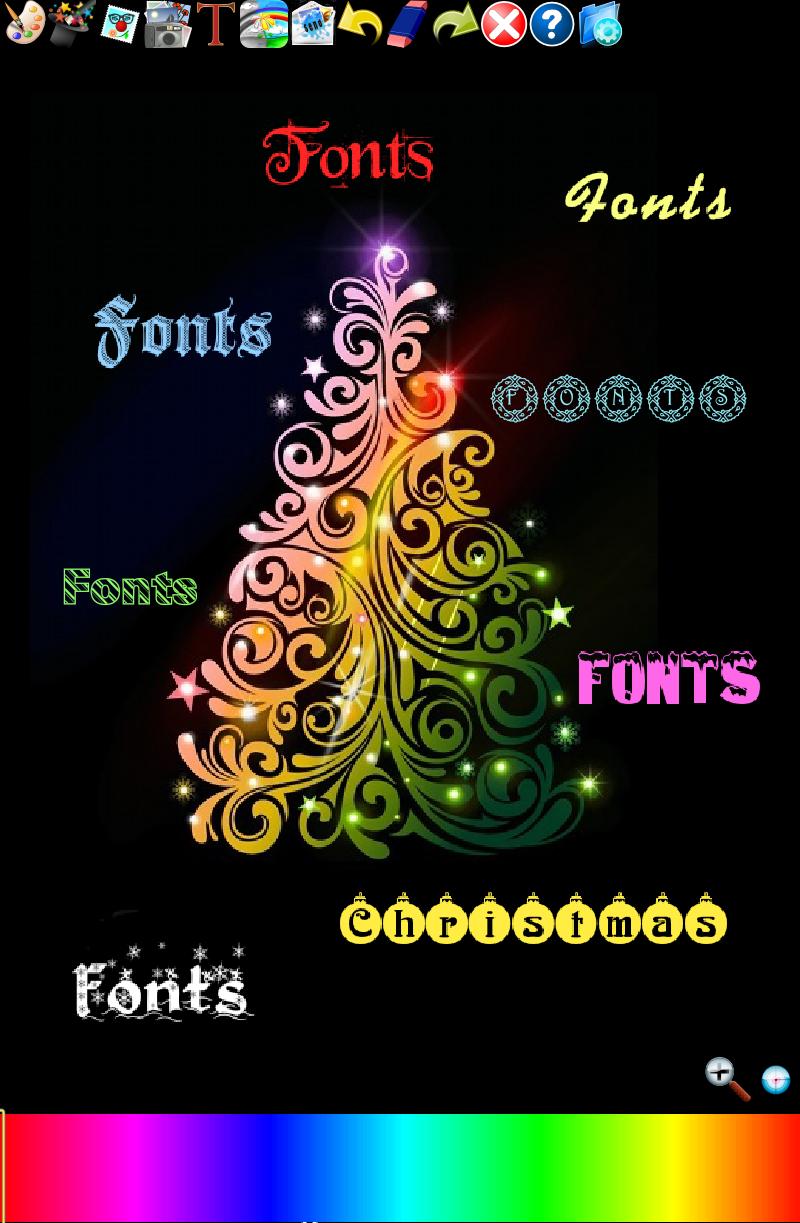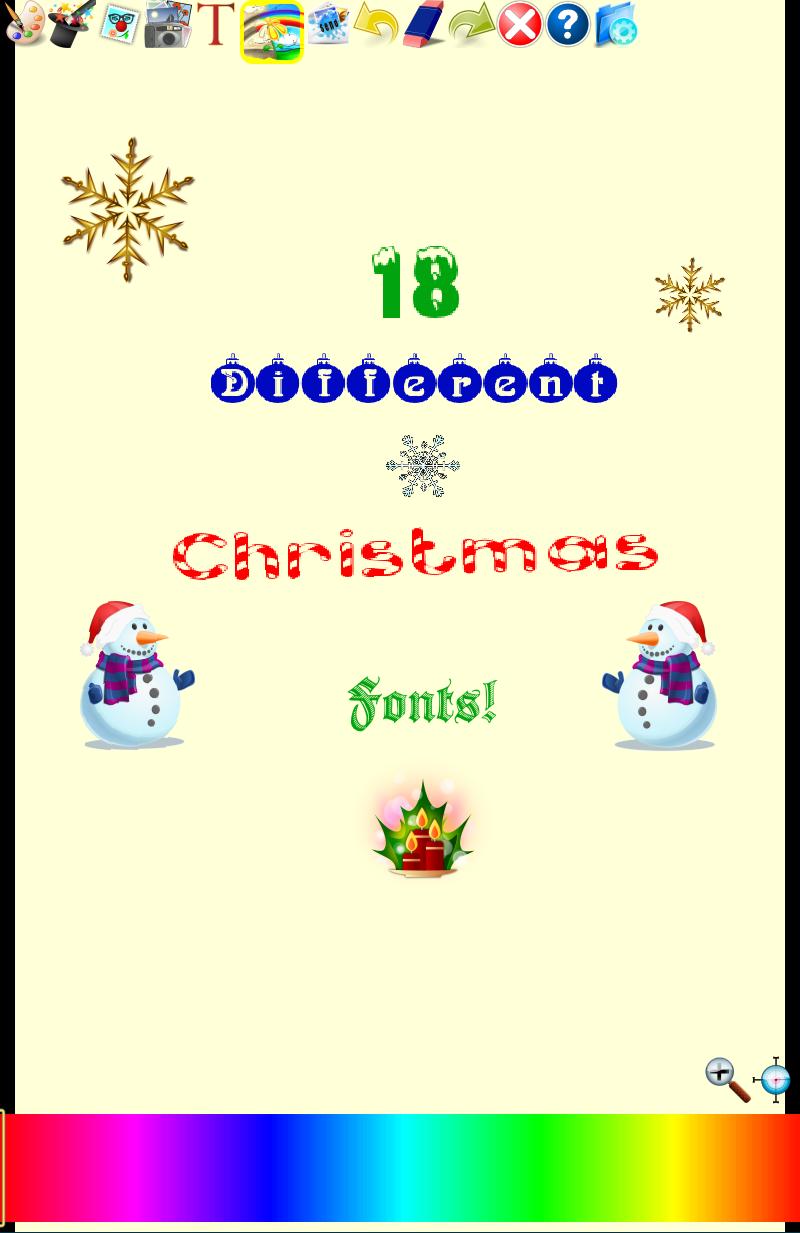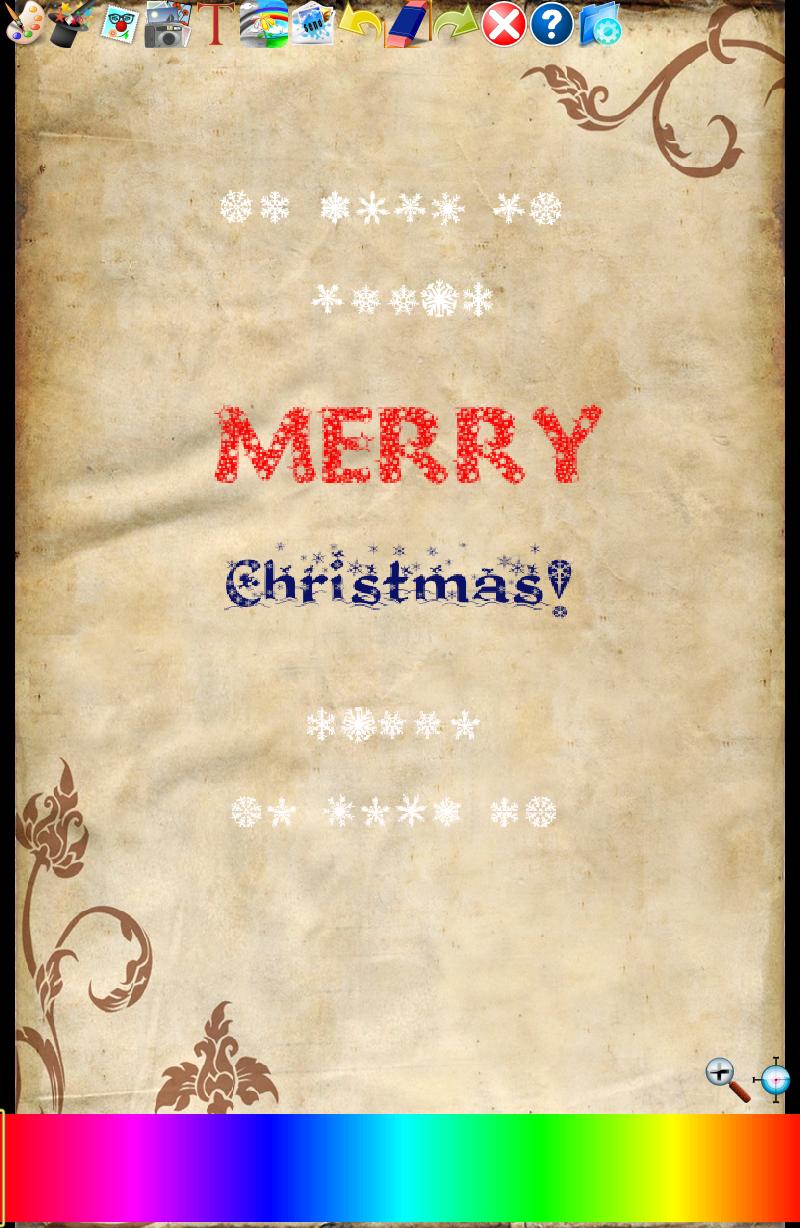
Christmas Fonts 4 Doodle Text!
ฟอนต์คริสต์มาส! Happy Doodle ส่งข้อความสุขสันต์วันคริสต์มาส!
ฟอนต์คริสต์มาสสำหรับข้อความดูเดิล! สุขสันต์วันคริสต์มาส!
หลังจากที่คุณติดตั้งฟอนต์คริสต์มาสแล้วคุณสามารถใช้เพื่อเขียนด้วยแบบอักษรสไตล์คริสต์มาสเหล่านี้ในสีที่แตกต่างกันคุณสามารถวาดด้วยคุณสมบัติข้อความแบบอักษรกราฟฟิตีภายในแอพ Doodle Text คุณเพียงแค่ต้องแตะที่คุณสมบัติปุ่มข้อความหรือคุณสมบัติข้อความ Doodle สเปรย์กราฟฟิตีภายใต้ปุ่ม Magic Hat และเลือก Font Pack จากนั้นเลือกแบบอักษรคริสต์มาสที่คุณต้องการใช้ สนุก!